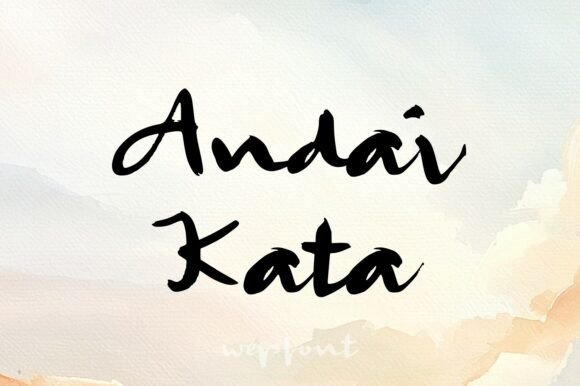
Andai Kata
適切なデザイン要素を見つけるのは難しい場合がありますが、Andai Kataは作品を即座に引き立てる優れたコレクションを提供します。
精密に作られたAndai Kataは、クリーンなベクター、滑らかなタイポグラフィ、そして安心のための商用ライセンスを提供します。
POD(オンデマンド印刷)製品、結婚式の招待状、またはソーシャルメディアのグラフィックを作成している場合でも、Andai Kataは理想的です。